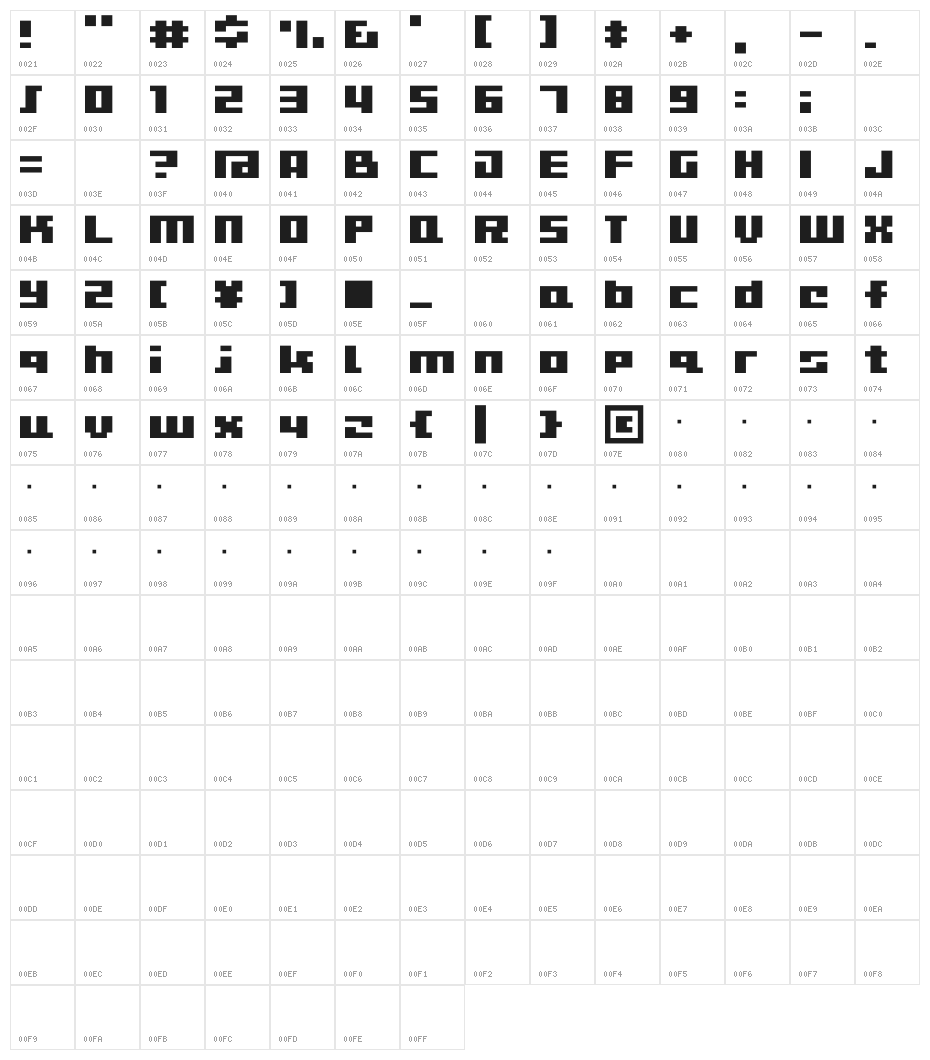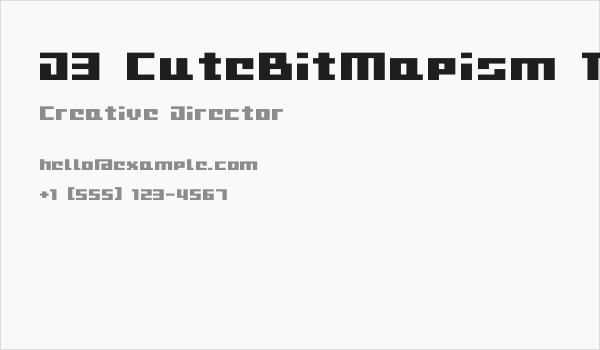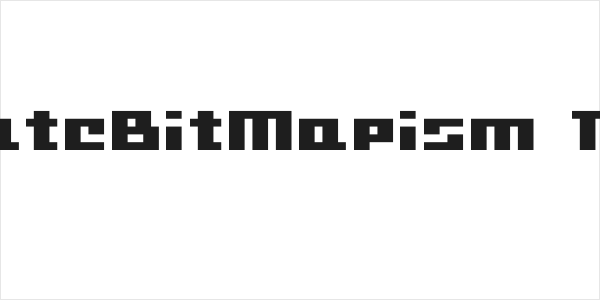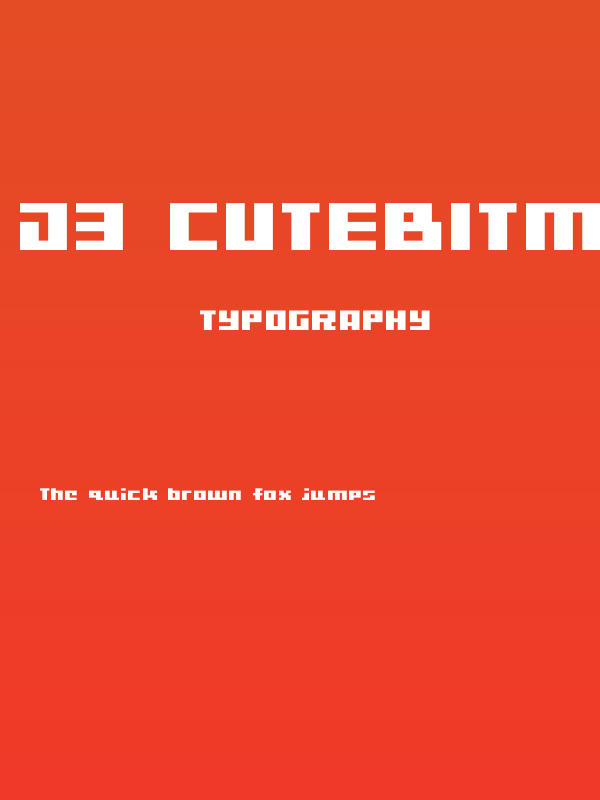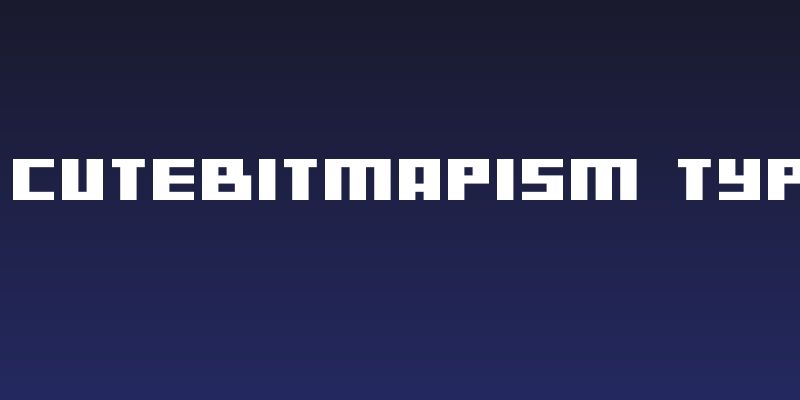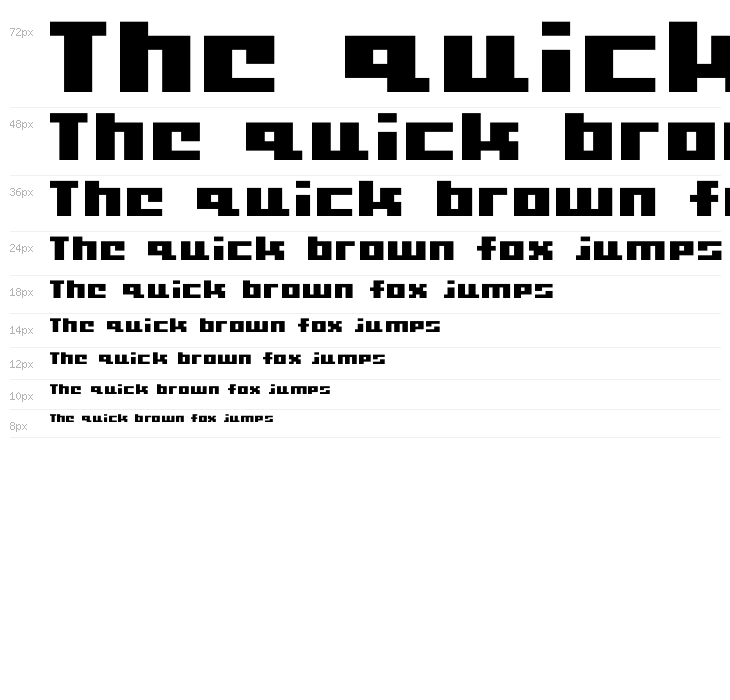
D3 CuteBitMapism TypeA Font
✎ Pixel
| Categorie | Pixel |
| Stile generale | Retro, Digital |
| Progetti proposti | Ideal for video game graphics, retro-themed posters, digital art projects, and tech-related branding. |